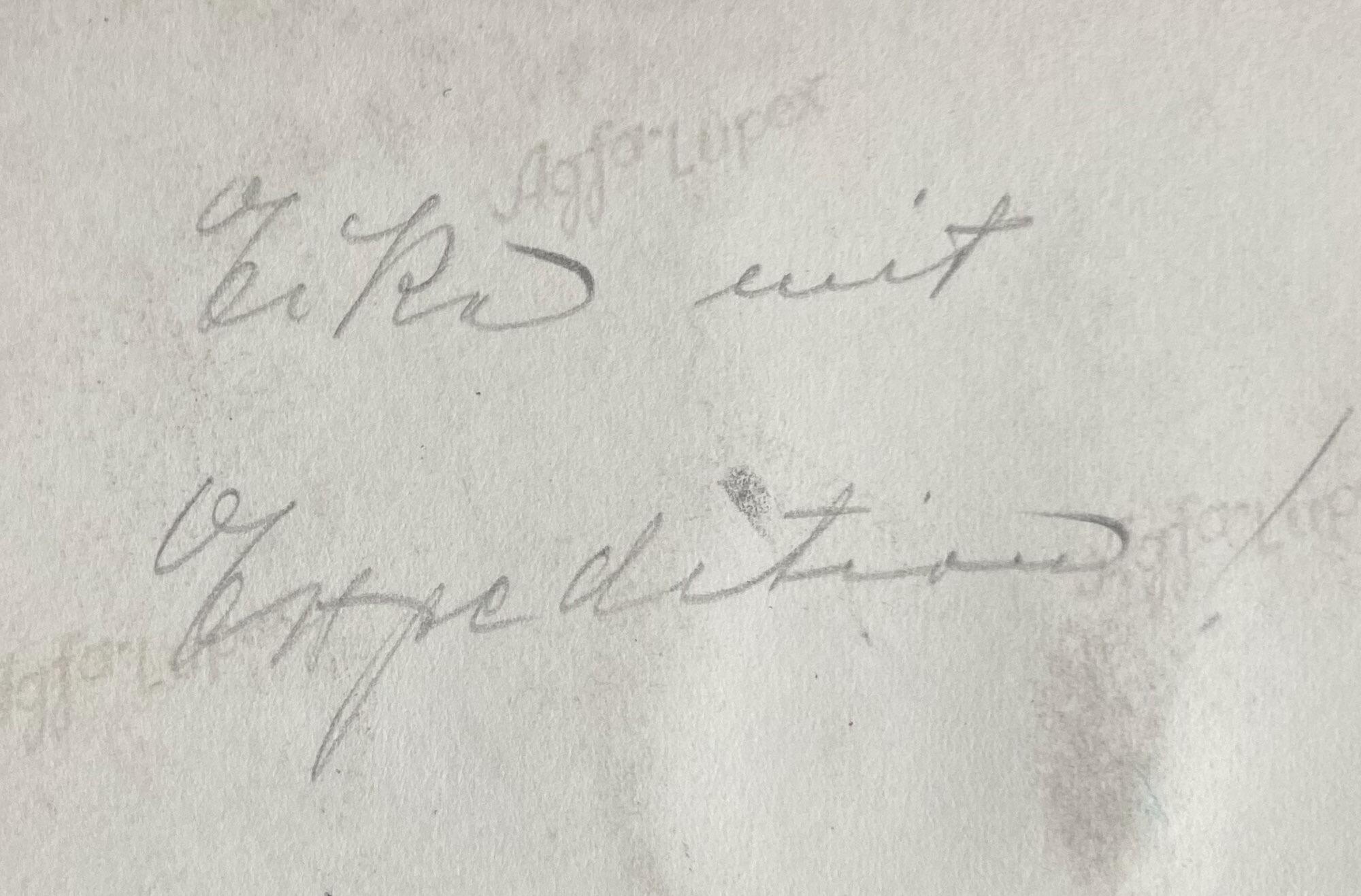
Wortentzifferung … mit Expedition
»Ecke« würde ich sagen. Es ist ja auch eine Häuserecke (eventuell mit Versand-/Vertriebsabetilung der Zeitung?) zu sehen.
Dass jemand das e unterschiedlich schreibt, wäre zumindest sehr ungewöhnlich. Sinn ergäbe die Ecke schon, »Expedition« war ja nicht nur Packerei/Versand, sondern auch die Anzeigenabteilung oder im weiteren Sinn die Zurschaustellung der Anzeigen im Schaukasten.
Ich hatte mal ein paar alte Postkarten aus der Zeit um 1900 erworben, da ging es auf fast jeder munter durcheinander mit Kurrent- und Lateinschrift, auch innerhalb eines Wortes. Auch die Handschrift meiner 1922 geborenen Mutter war z. B. prinzipiell lateinisch, viele ihrer Großbuchstaben waren es allerdings nicht …
Es wäre wohl spannend, mal halbwegs wissenschaftlich draufzuschauen, wie und wann die Koexistenz*/Vermischung/Wandel in der »deutschen« und »lateinischen« Handschrift aufgetreten sind. Vielleicht hat jemand Zeit … :party:
*) Beispielsweise begegnen einem ja mitunter lateinisch geschriebene Eigennamen innerhalb von Kurrenttexten …